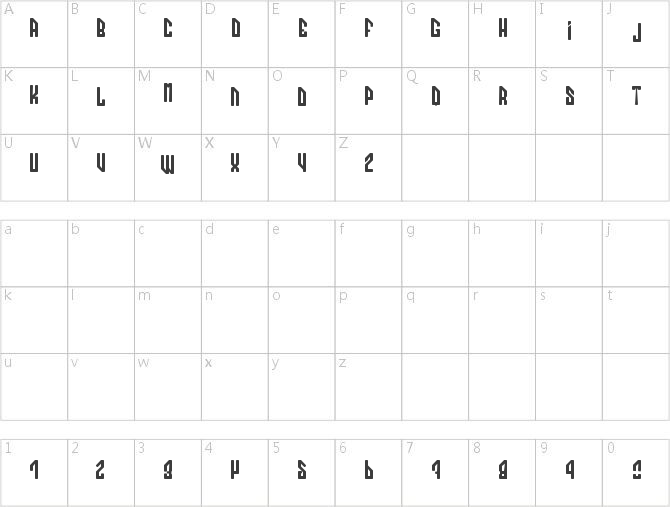
字體名稱: JACKIE
JACKIE TALK TO YOU !
JACKIE TALK TO YOU !字體字庫(kù)是一款讓人賞心悅目、百看不厭的英文字體,適合各類廣告和產(chǎn)品包裝設(shè)計(jì)應(yīng)用,字體大小0.02MB,格式為ttf字體,上傳用戶是sunlight,作者/版權(quán)方為未知